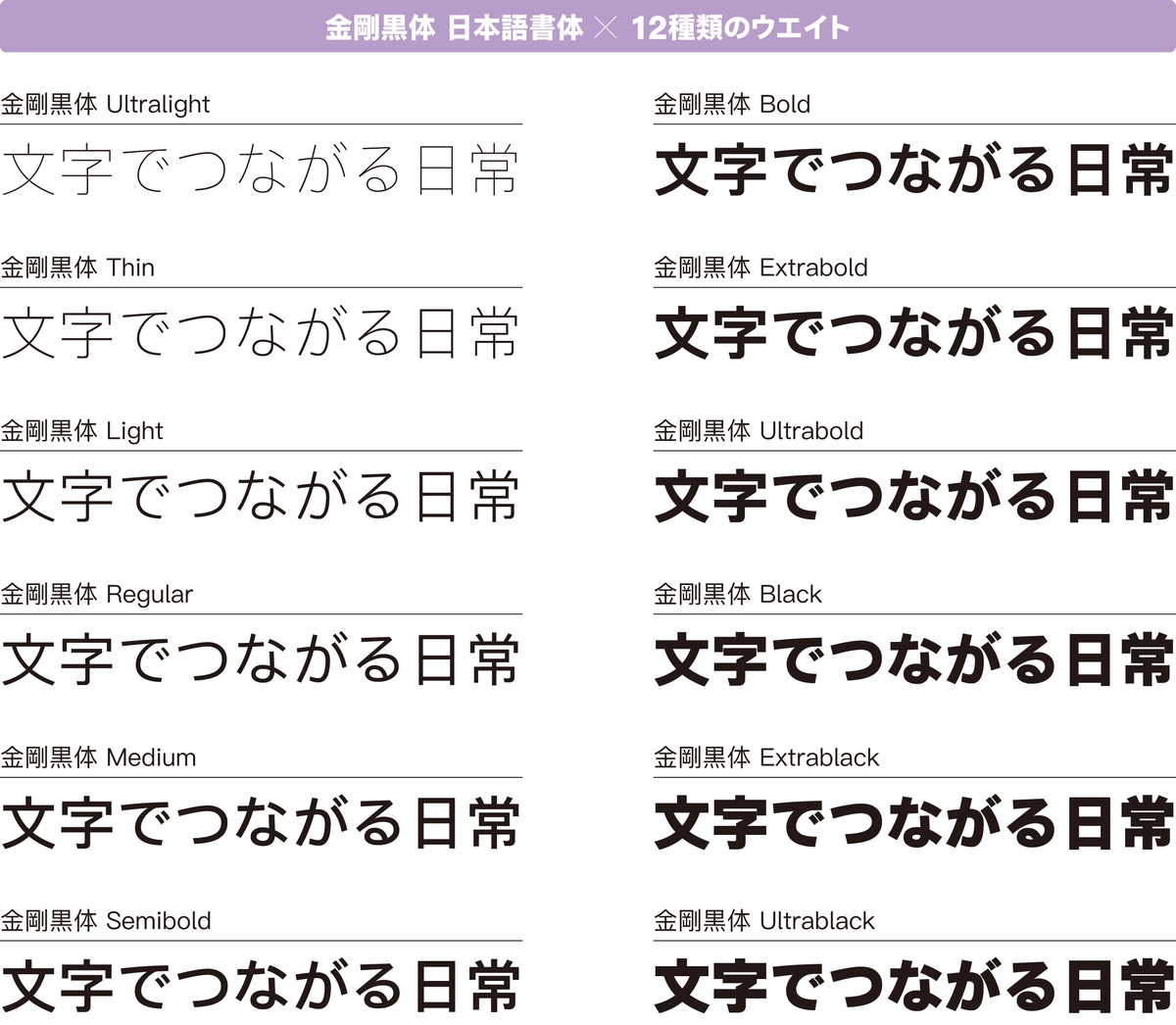
文字と絵師プロジェクト第2弾! 前田ミック×DynaFont金剛黒体とコラボレーションした オリジナルトートバッグを抽選で50名にプレゼント!
ダイナコムウェアは、人気絵師とDynaFont(ダイナフォント)のコラボレーションによりイラストと書体の魅力を最大限に高め合い表現する「文字と絵師プロジェクト」第2弾として、人気絵師・前田ミック氏(Twitter公式アカウント: @m_mic_0707 )とコラボレーションし、「文字でつながる日常」をテーマにダイナフォント「金剛黒体」を使用したオリジナルイラストを完成させ、2022年7月28日(木)~8月25日(木)の期間中に、抽選で50名に完成イラストをオリジナルトートバッグにしてプレゼントすることを発表した。
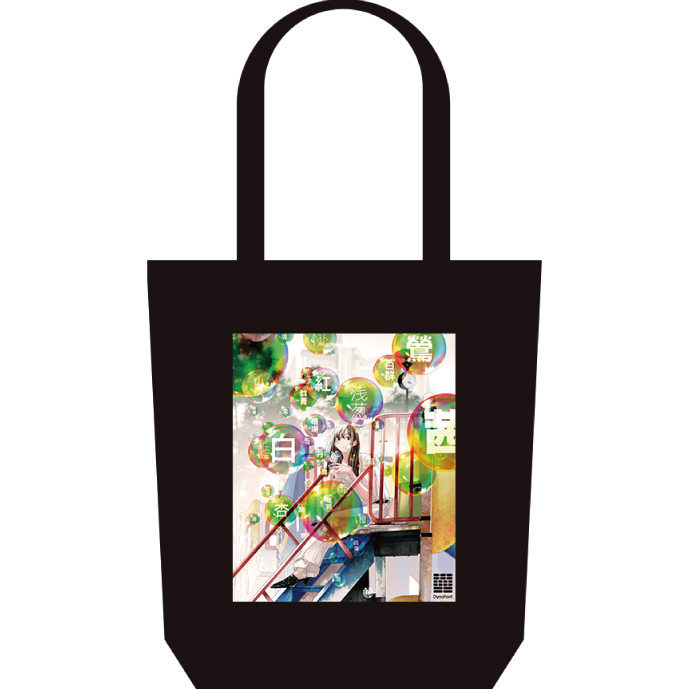
前田ミック×DynaFont金剛黒体コラボイラスト「文字でつながる日常」
「出現画廊 Creator's Show Up Gallery Online」にて開催の「DynaFontコンテスト」で「DynaFont賞」を受賞した人気絵師・前田ミック氏がダイナフォント「金剛黒体」を使用して「文字でつながる日常」をテーマに、イラストを制作した。
前田ミック×DynaFont金剛黒体コラボイラスト「文字でつながる日常」オリジナルトートバッグ
「文字でつながる日常」に使用したDynaFont金剛黒体
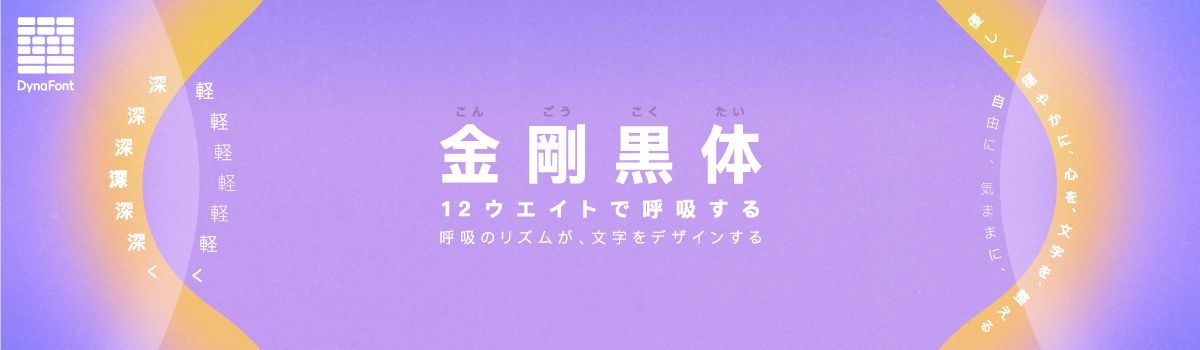
「金剛黒体」は、100ヶ国以上の国や地域のデジタルデバイスに対応可能な18言語で展開し、液晶表示での高い視認性、息吹を感じる柔らかな設計、各言語本来の美しさを追求したデザインにより、異なるインターフェースや言語においても人の温もりを以て情報を伝達できるゴシック体フォント。
日本語書体としても、これまで6ウエイトおよび、C90、C85、C80、C75の4種類のコンデンス書体をリリースしています。そのコンセプトやデザイン性は国内外で高い評価を受け、グッドデザイン賞など国際的なアワードを多数受賞してきた。
Ultralight、Thin、Light、Regular、Medium、Semiboldの6ウエイトで展開してきたが、さらに太いウエイトにも対応して欲しいというユーザーから寄せられる声を受け、Bold書体の開発を進め、2022年4月21日(木)より、Bold、Extrabold、Ultrabold、Black、Extrablack、Ultrablackの6ウエイトを、それぞれの太さに合わせた読み心地を追求した設計にてリリースした。